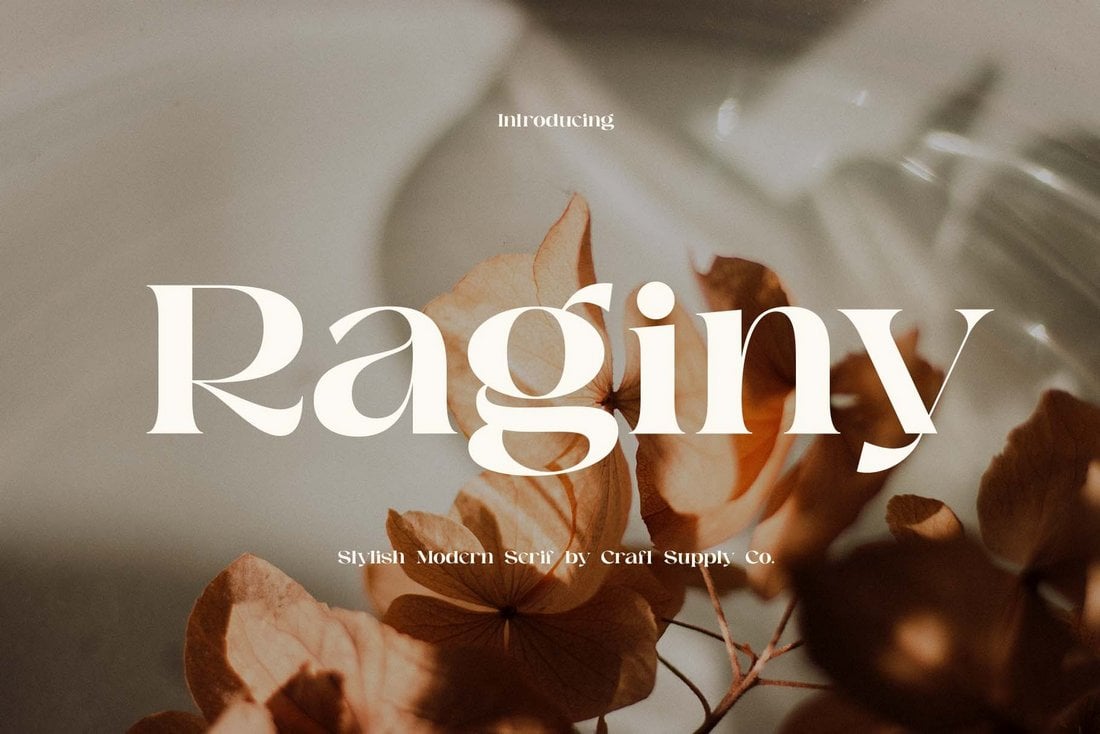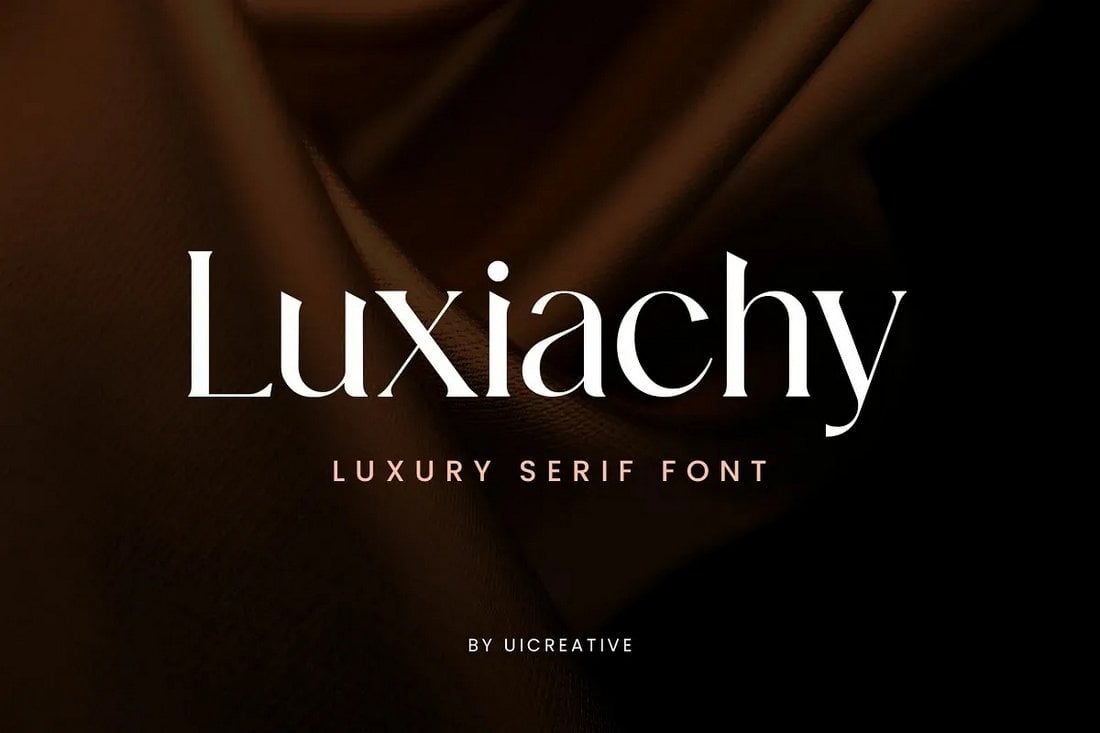
Wir sind beeindruckt von der Anzahl und Qualität der heute verfügbaren kostenlosen Schriftarten. Designer haben eine unglaubliche Auswahl an kostenlosen Schriftarten zur Verfügung. Egal, ob Sie eine Serifen-, Skript- oder Sans-Serif-Schriftart suchen, die heutige Sammlung der besten kostenlosen Schriftarten für Designer hat Sie abgedeckt!
Die Verwendung einer gut aussehenden Schriftart ist ein entscheidender Teil, um jedes Design professioneller wirken zu lassen. Natürlich müssen Sie nicht immer Premium-Schriftarten verwenden, um dasselbe Maß an Professionalität zu erreichen. Wenn Sie es sich nicht leisten können, Geld für Premium-Schriftarten auszugeben, um Ihre Designs großartig aussehen zu lassen, können Sie immer auf eine der Tausenden von kostenlosen Schriftarten zurückgreifen.
Diese Sammlung enthält die besten kostenlosen Skript-Schriftarten, Serifen-Schriftarten, Sans-Serif-Schriftarten, dekorative Schriftarten und vieles mehr, um zu jedem Designprojekt zu passen, an dem Sie arbeiten. Scrollen Sie nach unten und beginnen Sie mit dem Download. Die meisten Schriftarten sind kostenlos, mit einigen Premium-Optionen gemischt, wenn Sie nach etwas wirklich Herausragendem suchen.
Sangu - Kostenlose anspruchsvolle Serifenschriftart
Sangu ist eine wunderschöne Serifenschriftart mit anspruchsvollem Design. Sie hat einen perfekten Look für die Erstellung von Typografie-Designs im Zusammenhang mit moderner Mode, Lifestyle und Beauty-Marken. Die kostenlose Version der Schriftart ist für den persönlichen Gebrauch verfügbar.
Enoway - Kostenlose moderne Display-Schriftart
Diese Schriftart zeichnet sich durch ein modernes Buchstabendesign aus, das Ihrem Titel- und Überschriften-Design eine bestimmte Schönheit verleiht. Sie eignet sich ideal für alles, von Logo-Designs über Produktetiketten, Verpackungsdesigns und mehr. Sie ist kostenlos für den persönlichen Gebrauch.
NT Fabulous - Kostenlose moderne Serifenschriftart
Wenn Sie auf der Suche nach einer sauberen Serifenschrift für ein professionelles Projekt sind, ist diese Schriftart genau das Richtige für Sie. Sie kommt mit einem eleganten Serifenbuchstabendesign, das besonders für Unternehmens- und High-End-Marken geeignet ist.
Jaqueline - Kostenlose fette Skript-Schriftart
Mit wunderschön fließenden Zeichen wird Ihnen dieses kostenlose fette Skript dabei helfen, schöne Titel und Texte für Ihre Grußkarten, Visitenkarten und Hochzeitseinladungen zu gestalten. Es ist kostenlos für die Verwendung in persönlichen Projekten.
Gilmoray - Kostenlose elegante Sans-Serif-Schriftart
Der klar geschnittene Look der Buchstaben der Schrift verleiht ihm einen sehr professionellen Look und ein Gefühl. Es passt gut zu Magazin-Covern, Postern, Anzeigen und verschiedenen anderen Designs. Es ist kostenlos für den persönlichen Gebrauch.
Luxiachy - Kostenlose luxuriöse Serifenschriftart
Machen Sie Ihre Logos und Titel mit dieser kostenlosen Serifenschriftart luxuriös und teuer. Sie kommt mit einem eleganten Buchstabendesign für die Gestaltung von Designs für High
-End-Marken. Die Schriftart ist kostenlos für die Verwendung in persönlichen Projekten.
Raginy - Kostenlose stilvolle Serifenschriftart
Eine weitere elegante und stilvolle Serifenschriftart, die Sie kostenlos herunterladen können. Diese Schriftart eignet sich am besten für Mode- und Lifestyle-Designs, um aufmerksamkeitsstarke Titel hinzuzufügen. Sie ist kostenlos zum Download und zur Verwendung in persönlichen Projekten.
Lemonade - Kostenlose stilvolle Serifenschriftart
Lemonade ist eine kreative Skript-Schriftart mit einem einzigartigen handgeschriebenen Buchstabendesign. Diese Schriftart eignet sich ideal für Grußkarten und sogar Branding-Designs. Sie ist kostenlos für den persönlichen Gebrauch.
Roklin - Kostenlose klassische Schriftart
Diese klassische und stilvolle Schriftart eignet sich perfekt für viele verschiedene Arten von Titel- und Überschriften-Designs. Sie können sie für die Gestaltung von Typografie für alles von Postern bis zu individuellen T-Shirts und sogar Markenlogos verwenden.
Longies - Kostenlose Retro-Groovy-Schriftart
Diese kostenlose Schriftart hat ein sehr markantes Buchstabendesign, das von den typografischen Designs der 1960er und 70er Jahre inspiriert ist. Die Schriftart eignet sich perfekt für Schilderdesigns und Verpackungsdesigns.
Strong Heart - Kostenlose handgeschriebene Schriftart Duo
Dies ist ein Zwei-in-Eins-Schriftart-Duo, das sehr gut zusammenpasst. Die kostenlose Version der Schriftart enthält die handgeschriebene Schrift aus diesem Paar und eignet sich perfekt, um Ihren Designs einen persönlichen Look zu verleihen.